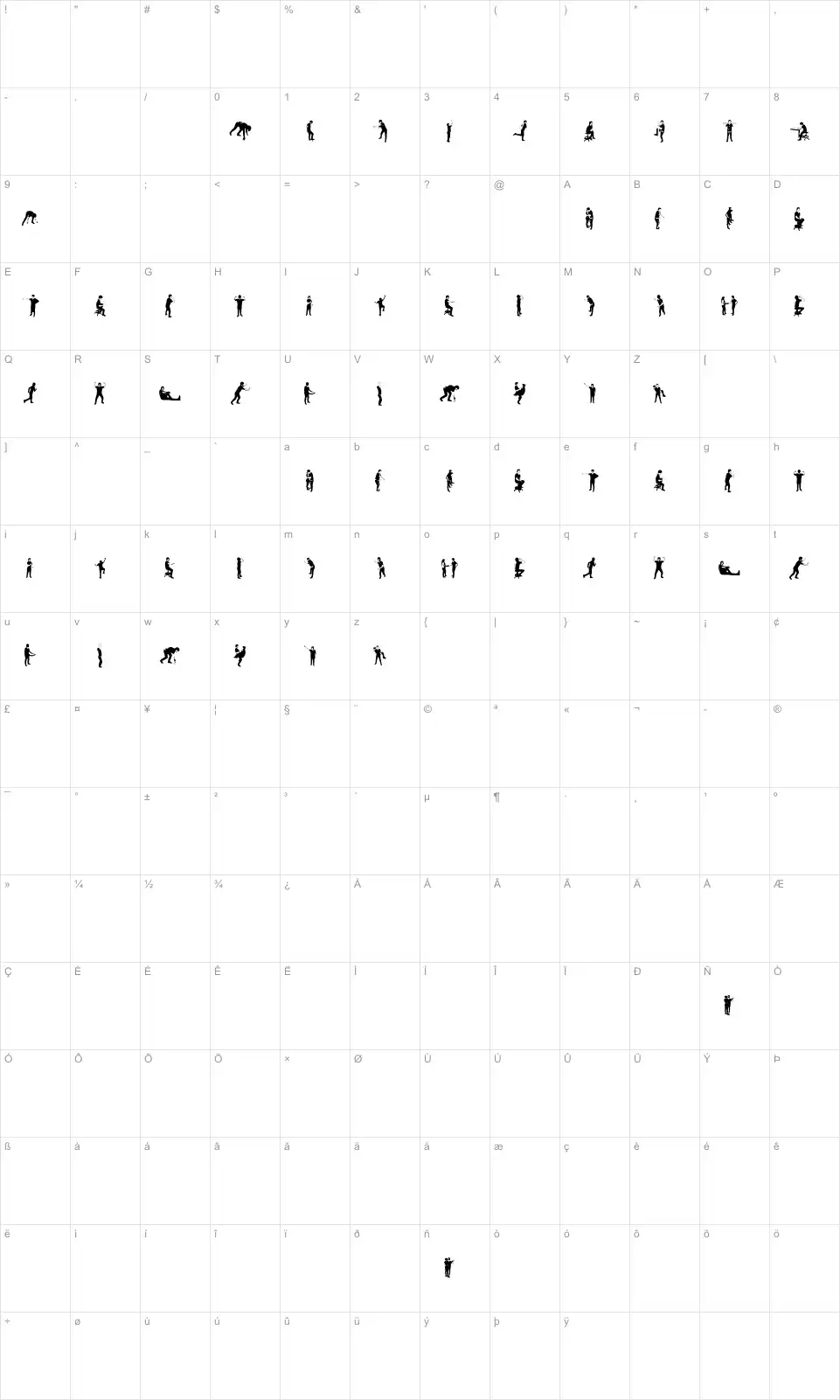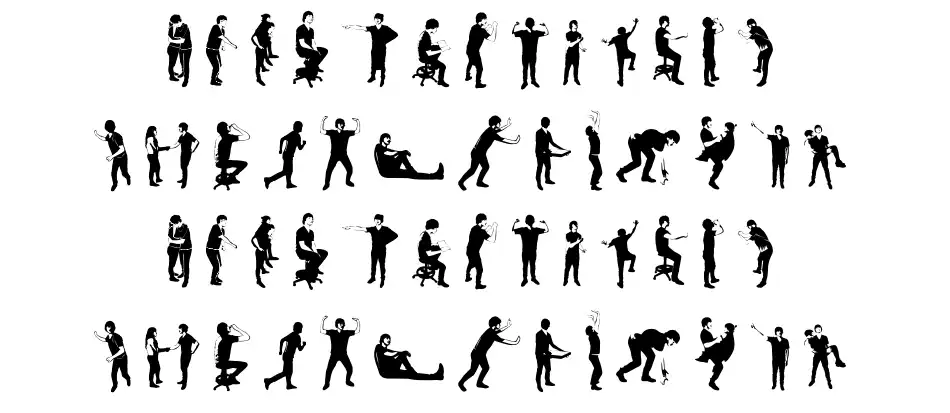
Accion Dingbat Tipografia – Fonte Grátis
Accion Dingbat Tipografia
A Accion Dingbat Tipografia é uma fonte divertida e versátil criada por Diseño y Empresa, ideal para adicionar um toque único a seus projetos gráficos. Esta fonte pertence à categoria de Dingbats e é um excelente recurso para designers e criativos que buscam algo diferente e atraente para suas obras. Seja para criar logotipos, infográficos ou design de materiais impressos, a Accion Dingbat Tipografia pode ser o elemento que seu projeto precisa para se destacar. Com um formato TTF, a fonte está disponível para download, permitindo que você experimente a funcionalidade desta fonte antes de incluí-la em seus projetos. Desde sua adição em 12 de julho de 2022, a Accion Dingbat Tipografia já tem recebido elogios por seu design único, que é ideal para aqueles que procuram algo um pouco diferente e divertido para seus designs. Com apenas 54 KB de tamanho, a fonte é de fácil acesso e ideal para uso em qualquer dispositivo.
Mapa de caracteres da fonte Accion Dingbat Tipografia